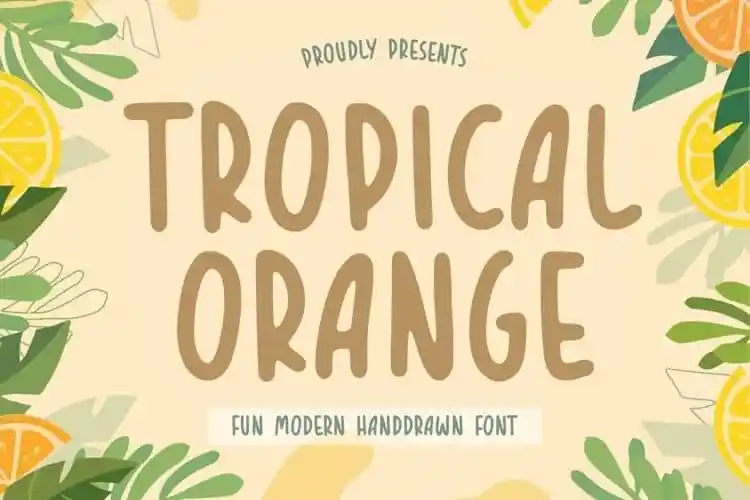
TROPICAL ORANGE Handdrawn Font – Download Grátis
TROPICAL ORANGE é uma elegante fonte de letra manuscrita ideal para variados projetos criativos. Perfeita tanto para elementos visuais dos produtos e embalagens, quanto para branding, revistas, mídias sociais, eventos casamentos ou simplesmente para destacar frases sobre um fundo. Essa fonte carrega o calor e a frescura da baía em que o sol se por, transmitindo uma sensação de leveza e vivacidade. Ela transmite um ar descontraído e despojado, tornando-se um escolher perfeito para trabalhos criativos onde o design deve ser mais expressivo do que formal. Com certeza não hesite em incluí-la nas suas próximas criações digitais.